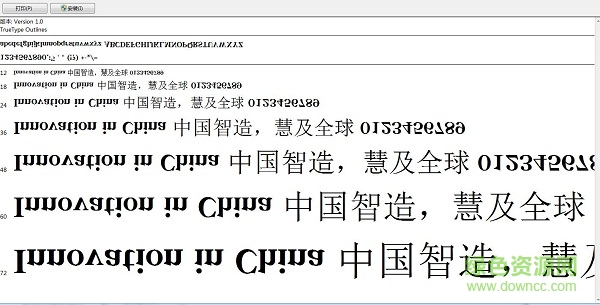
menksoftgarqag_mirror字體是一款由蒙科立官方推出的蒙文字體,字形簡(jiǎn)約又不缺力量感,清朗有勁,識(shí)別性教強(qiáng),可以用于商場(chǎng)海報(bào)、網(wǎng)站設(shè)計(jì)等領(lǐng)域,需要的朋友快來(lái)下載吧!
蒙古文字是經(jīng)過(guò)腓尼基字母--- 阿拉米字母 --- 粟特字母 --- 畏兀兒字母這樣一個(gè)漫長(zhǎng)的演變過(guò)程的。它從上到下連寫(xiě)(一個(gè)單詞為一個(gè)單位),從左到右移行。